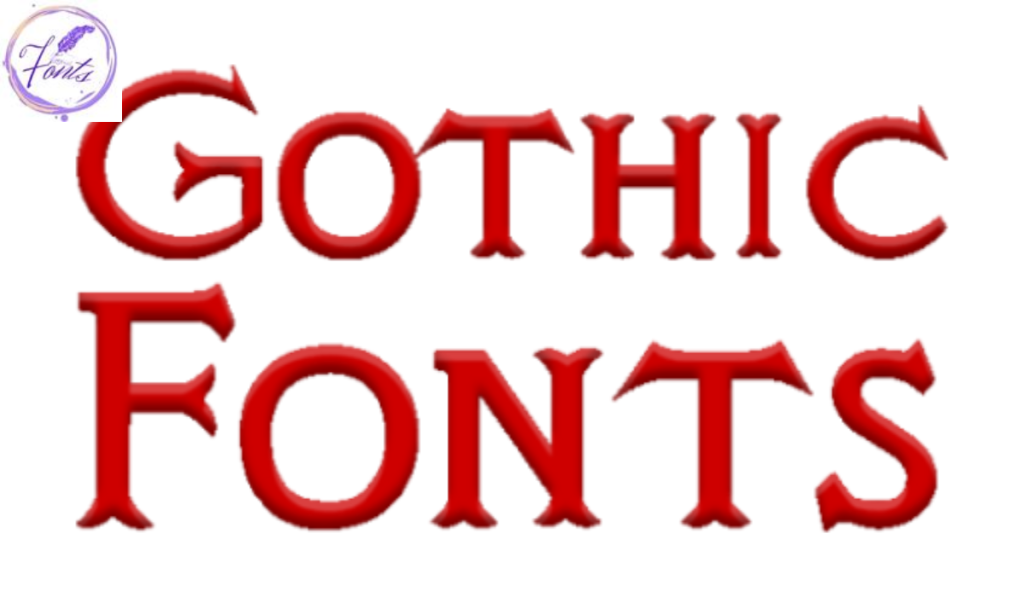
Top 10 font chữ Gothic Việt hóa La Mã thời kỳ Roman
Phân loại: Cổ điển, cá tính
Kiểu chữ: Có chân
Khi nói đến việc mang lại sự quyến rũ bí ẩn cho các thiết kế, font chữ gothic là sự lựa chọn không thể bỏ qua. Font Gothic Việt hóa không chỉ giúp thể hiện sự tinh tế, mà còn bổ sung một chút cổ điển, gợi nhớ đến phong cách kiến trúc và nghệ thuật châu Âu từ thời trung cổ. Sự đa dạng của font chữ gothic giúp nó phù hợp với nhiều loại hình thiết kế từ sách báo, trang web cho đến thiết kế logo và nhiều hơn nữa.
Top 10 font chữ Gothic Việt hóa thời kỳ La Mã Roman
Font Gothic lãng mạn – Angel Wish Font
Font Angel Wish là một kiểu chữ Gothic mang đậm tính lãng mạn và nghệ thuật, nổi bật với những đường cong mềm mại và nét vẽ tinh tế. Được thiết kế để tạo cảm giác ấm áp, Angel Wish là lựa chọn lý tưởng cho các dự án liên quan đến tình yêu, sự nhẹ nhàng và hạnh phúc. t
Font Gothic cổ điển – Font Chomsky
Font Chomsky là một kiểu chữ Gothic cổ điển, kết hợp giữa vẻ đẹp truyền thống và sự hiện đại, được lấy cảm hứng từ triết lý của nhà ngôn ngữ học nổi tiếng Noam Chomsky. Với những đường nét sắc sảo và cấu trúc độc đáo, font này không chỉ mang lại sự trang trọng mà còn thể hiện chiều sâu tư tưởng trong mỗi tác phẩm. Sự kết hợp này tạo ra một phong cách riêng biệt, phù hợp cho các thiết kế yêu cầu sự tinh tế và đẳng cấp.
Font Gothic hiện đại – Font The Blowar
Font The Blowar là một kiểu chữ Gothic mạnh mẽ, được thiết kế bởi Alit Design, nổi bật với những đường nét đậm và ấn tượng, phù hợp cho các tiêu đề phim anh hùng, thiết kế logo và áo thun.
Font Gothic UVN Hoa Ky
Font UVN Hoa Ky là một kiểu chữ Gothic Việt hóa, được thiết kế nhằm kết hợp vẻ đẹp cổ điển với tinh thần tự do và mạnh mẽ của văn hóa Hoa Kỳ. Với những đường nét sắc sảo và phong cách độc đáo, font này không chỉ mang lại sự trang trọng mà còn thể hiện sự sáng tạo trong các tác phẩm thiết kế. Sự kết hợp giữa truyền thống và hiện đại khiến UVN Hoa Ky trở thành lựa chọn lý tưởng cho các dự án cần sự nổi bật và cá tính trong thiết kế đồ họa.
Font UTM Dai Co Viet
Font UTM Dai Co Viet là một kiểu chữ Việt hóa mang đậm ảnh hưởng văn hóa truyền thống, kết hợp giữa nét cổ điển và sự hiện đại, phù hợp cho nhiều thiết kế đồ họa. Với những đường nét mềm mại và uyển chuyển, font này không chỉ tạo cảm giác gần gũi mà còn thể hiện sự tinh tế trong từng tác phẩm.
Font MTD Black Baron Gothic Việt hóa
Font MTD Black Baron Gothic Việt hóa là một kiểu chữ mạnh mẽ và ấn tượng, mang đậm phong cách Gothic với những đường nét sắc sảo và cá tính. Được thiết kế để phù hợp với các dự án sáng tạo, font này không chỉ tạo ra sự nổi bật mà còn thể hiện được tính nghệ thuật trong từng tác phẩm. Sự kết hợp giữa vẻ đẹp cổ điển và hiện đại giúp MTD Black Baron Gothic trở thành lựa chọn lý tưởng cho các thiết kế logo, tiêu đề và ấn phẩm quảng cáo.
Font Gothic nét mảnh – MTD Briliants Typeface
Font MTD Briliants Typeface Việt hóa là một kiểu chữ Script mang phong cách cổ điển, được thiết kế với những đường nét thanh thoát và tinh tế. Được Việt hóa bởi Mộc Hạ, font này không chỉ mang lại sự sang trọng mà còn thể hiện được sự sáng tạo trong các tác phẩm thiết kế, phù hợp cho nhiều loại hình như video âm nhạc, banner quảng cáo và các ấn phẩm in ấn.
Font Gothic thư pháp – MTD Geza Script
Font MTD Geza Script là một kiểu chữ Việt hóa mang phong cách thư pháp, nổi bật với những đường nét mềm mại và uyển chuyển, tạo cảm giác gần gũi và nghệ thuật.
Font Old London
Font Old London là một kiểu chữ Gothic cổ điển, mang phong cách Anh quốc thế kỷ 19, với những đường nét tinh tế và ấn tượng. Được thiết kế để tạo cảm giác trang trọng và sang trọng, font này thường được sử dụng trong các ấn phẩm in ấn cao cấp như thiệp cưới, menu nhà hàng và các tác phẩm nghệ thuật, mang lại sự độc đáo và ấn tượng cho mỗi thiết kế.
Pieces of Eight Font
Font Pieces of Eight là một kiểu chữ Gothic hiện đại, được thiết kế bởi Steve Ferrera, mang đến sự kết hợp hoàn hảo giữa phong cách cổ điển và hiện đại. Với những đường nét mạnh mẽ và tinh tế, font này phù hợp cho nhiều ứng dụng thiết kế, từ tiêu đề đến logo, giúp tạo ra ấn tượng nổi bật và thu hút.